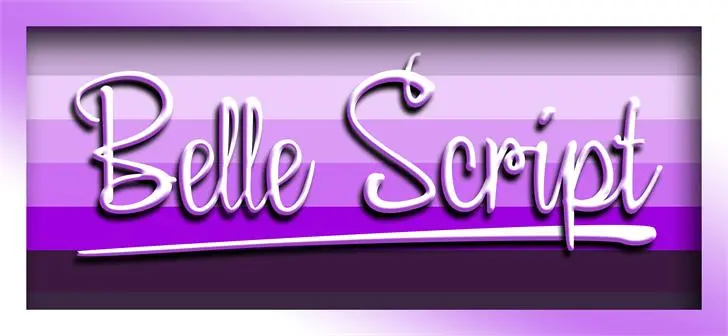
A Belle Script Font é uma fonte elegante e artesanal projetada pelo designer Hamilton, trazendo um toque pessoal e criativo à sua escrita. Suave e sofisticada ao mesmo tempo, esta fonte transmite um sentimento quase mágico de delicadeza e sutileza. Ela é ideal para estilos de design que valorizam a mão na escrita, dando vida a letras autênticas e emocionantes. Seja em cartões de aniversário, publicações editoriais ou até mesmo para um pequeno apontador pessoal, esta fonte pode tornar sua obra ainda mais única e especial. Além disso, não se esqueça de contribuir através do PayPal no endereço  para manter esta bela fonte disponível para todos. A cada centavo que você doar, você está também dando um pouquinho de você à arte deste design encantador. Compre agora e faça a Belle Script Font sua escolha personalizada para suas próximas criações.